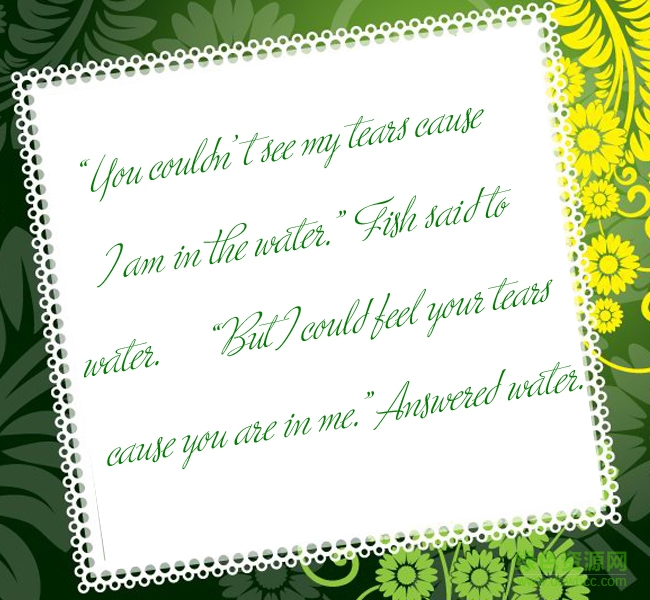
ministry英文字體
ministry字體是一款英文字體軟件,字體十分飄逸,猶如中文字體草書般,行如流水,非常好看,用戶英文創(chuàng)意設計再合適不過了,更多類似字體盡在綠色資源網(wǎng)!
ministry英文字體介紹
ministry字體屬于英文字體中的草書,字形清秀大方,華而不浮,非常適合廣告設計、平面設計、印刷包裝、正文標題等人員使用。